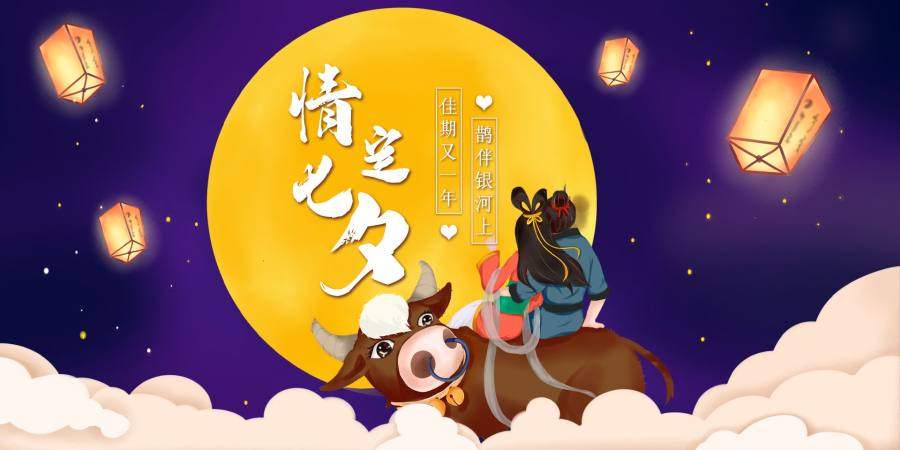
如何让你的七夕借势海报突出重围,一款合适的字体自然是少不了的啦!
汉标高清锐毛书法味道的纯手写字体,作者运用大号毛笔精心书写,楷书味道浓厚,由于字体较大,使得笔画清晰度较高,笔画中也减少了过多的处理和笔势,厚重、饱满。因为是纯手写的原因,它独特的气质更与其他字体不同,看似统一,其实各有各的味道,每个字都可以独具风情。